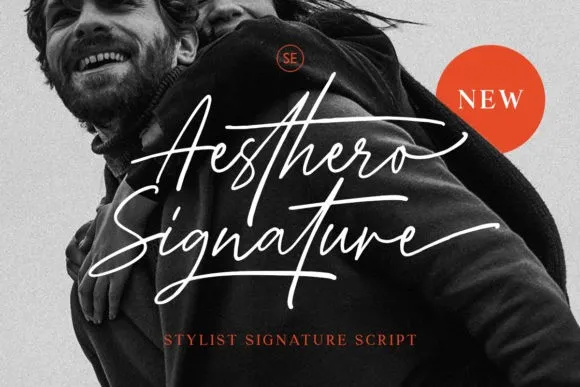
A Aesthero Font é uma elegante e fluida fonte escrita à mão que integra letras minúsculas, maiúsculas, símbolos e suporta múltiplas línguas. Este tipo de letra foi projetada pelo designer Saridezra, contendo recursos avançados como ligaturas, alternativas contextualas e estilizadas, bem como swashes para um gráfico completo e atraente. Aesthero é ideal tanto para assinatura de logotipo em design fashion elegante, quanto para criações únicas para cartões de casamento ou citações escritas à mão. Com sua codificação PUA (Propriedade Universal do Alfa), essa fonte oferece uma funcionalidade poderosa e versátil que atende a uma ampla variedade de aplicativos, tornando-a ideal para designers buscando expressar seus trabalhos em estilos distintos e criativos.